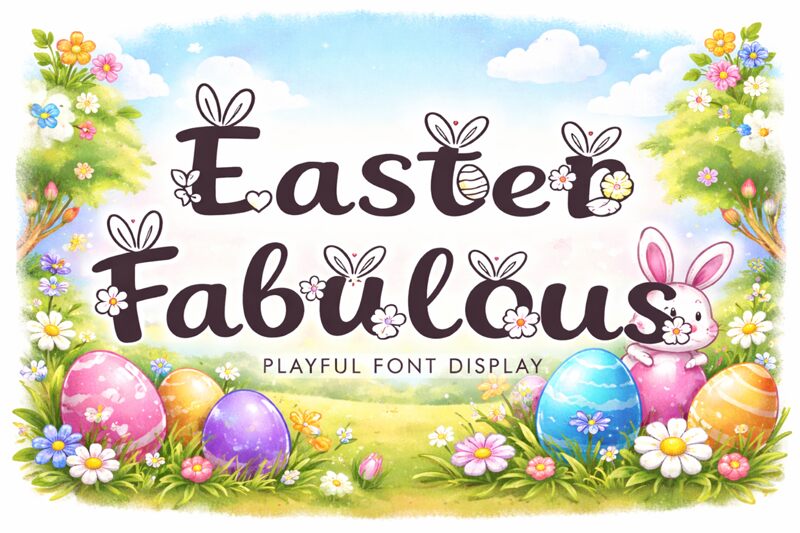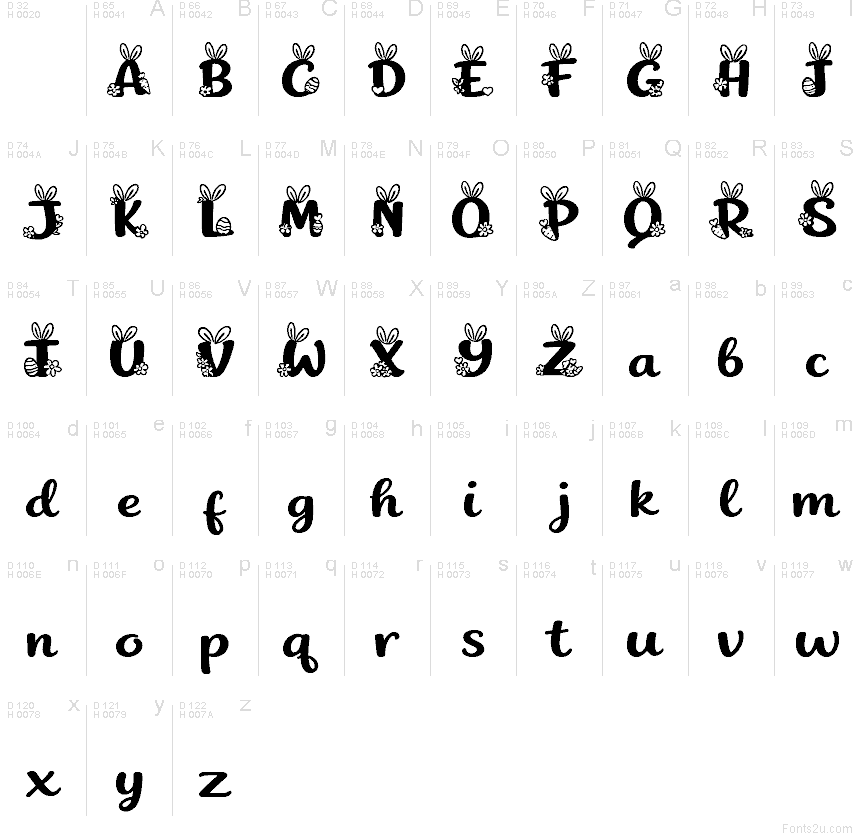
Easter Fabulous Demo
Easter Fabulous da Yoga Letter é uma fonte gratuita de Páscoa com letras manuscritas arredondadas e um caractere inicial decorativo que transforma qualquer texto em um motivo festivo. As formas fluidas, curvas suaves e os pequenos detalhes florais e de coração conferem-lhe o aspecto de um cartão de felicitações feito à mão, sem perder a leveza.
Easter Fabulous é perfeita para convites de Páscoa, panfletos de eventos de primavera, etiquetas artesanais, embalagens de padaria, etiquetas de presente e gráficos festivos para redes sociais. Os seus detalhes temáticos são especialmente eficazes quando deseja que um título curto ou uma frase de destaque pareça sazonal e pessoal.